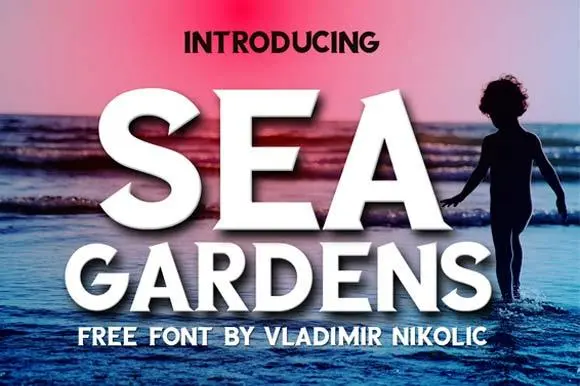
Sea Gardens Typeface – Download Grátis
Aqui está uma breve descrição para a página de download da fonte “Sea Gardens Typeface”, no português do Brasil: Sea Gardens é uma fonte serif com estilo retro, criada pelo talentoso designer Hamilton. Com suas linhas elegantes e detalhes distintos, esta fonte se adapta perfeitamente para gráficos retro ou vintage. Ela é especialmente adequada para criações de logotipos, títulos e posters, proporcionando um toque nostálgico a qualquer projeto. Suas características sólidas oferecem uma excelente resolução em diversos formatos de mídia digital. Ideal tanto para utilização em impressão quanto no design online, Sea Gardens é perfeita para aqueles que desejam agregar um ar retrô aos seus projetos, seja para publicidade, marca ou qualquer outra aplicação visual que valorize a nostalgia. Com seu conjunto completo de símbolos e uma variedade de tamanho, esta fonte oferece uma ampla gama de possibilidades. Para designers e criadores de conteúdo em busca de um toque vintage sem abrir mão da precisão moderna, Sea Gardens é uma escolha perfeita.